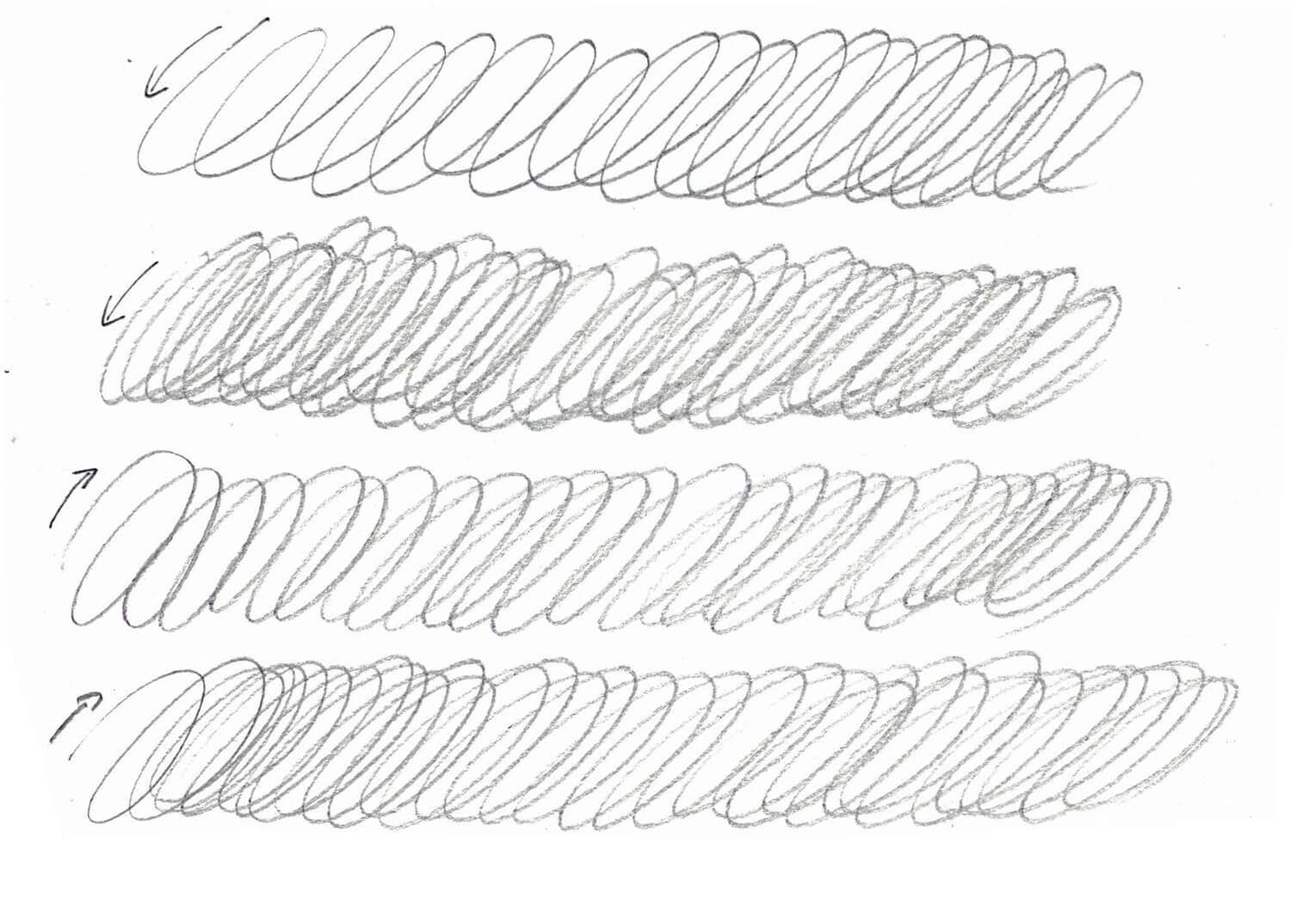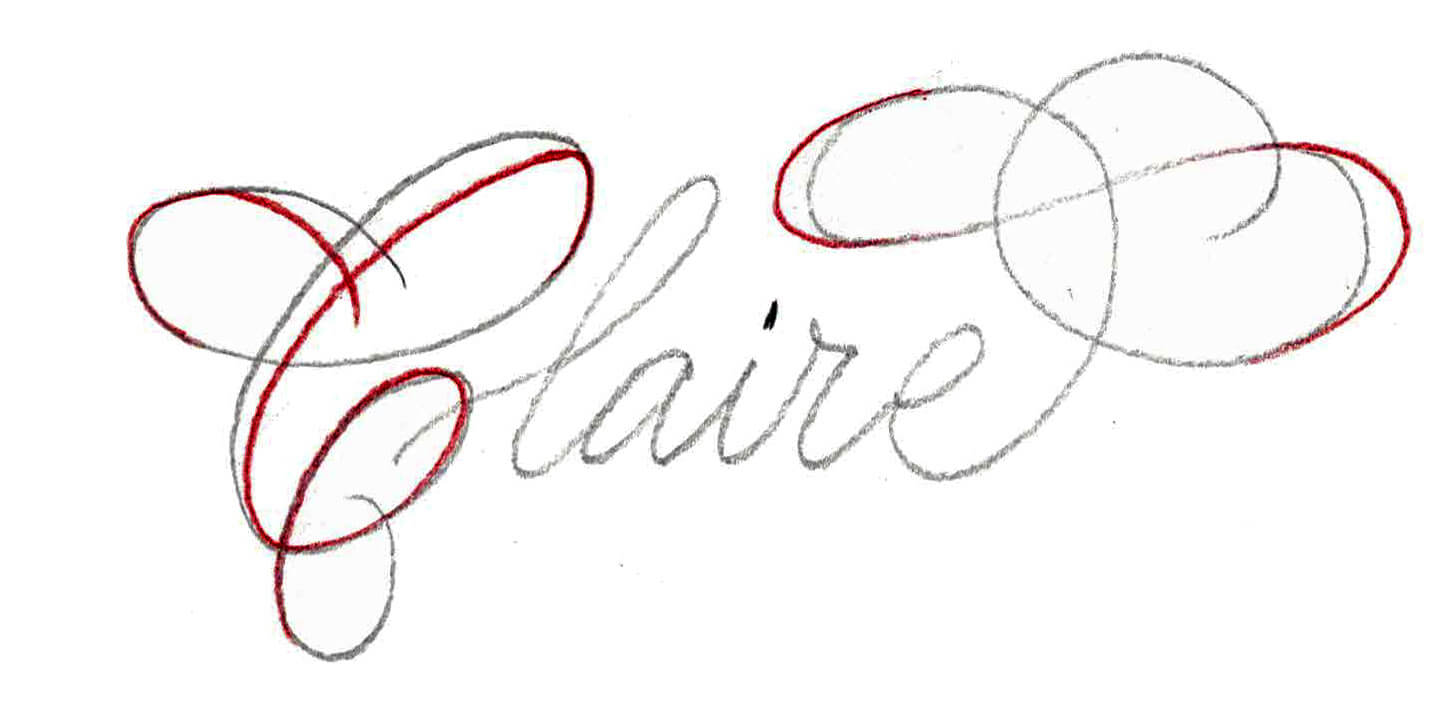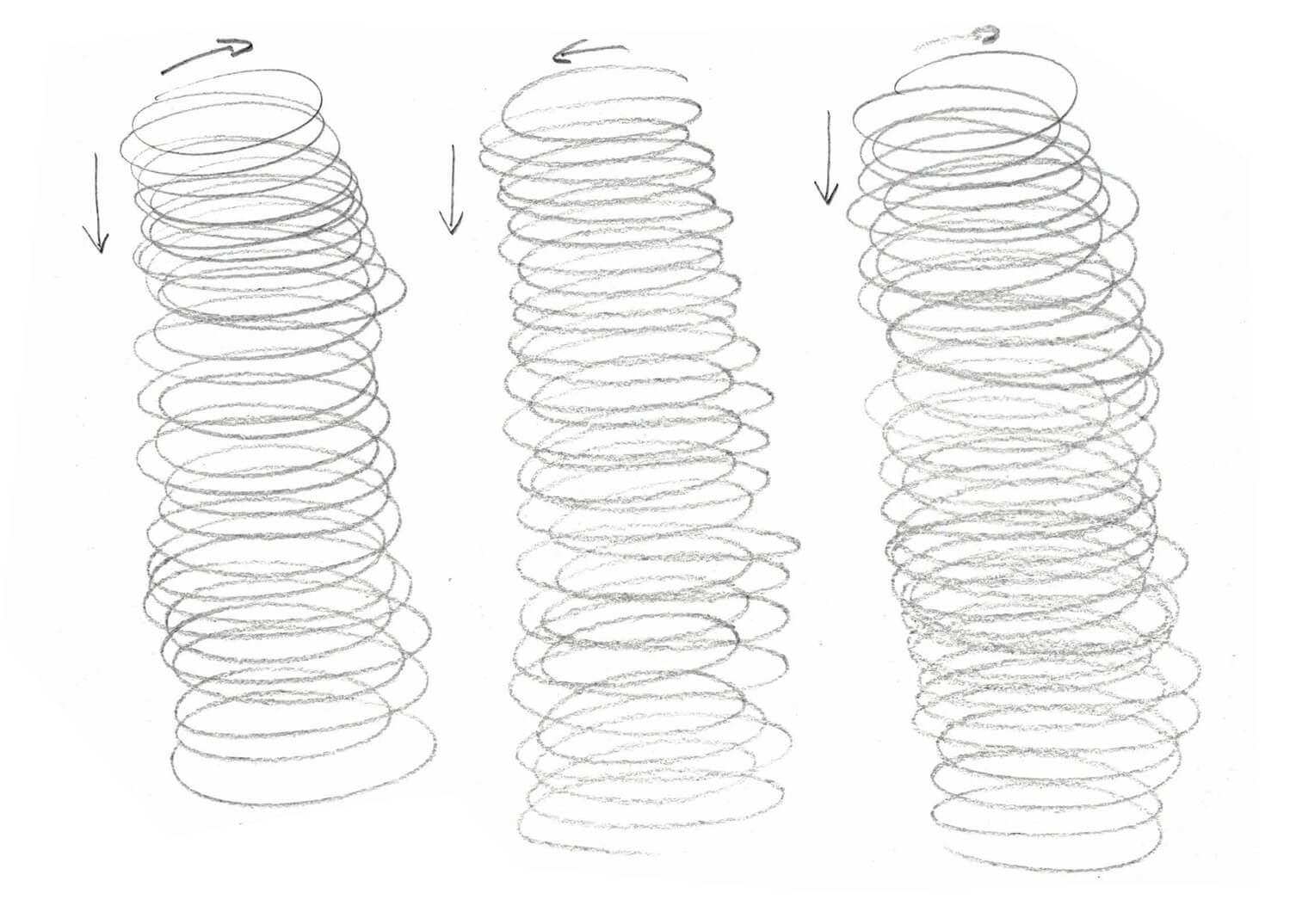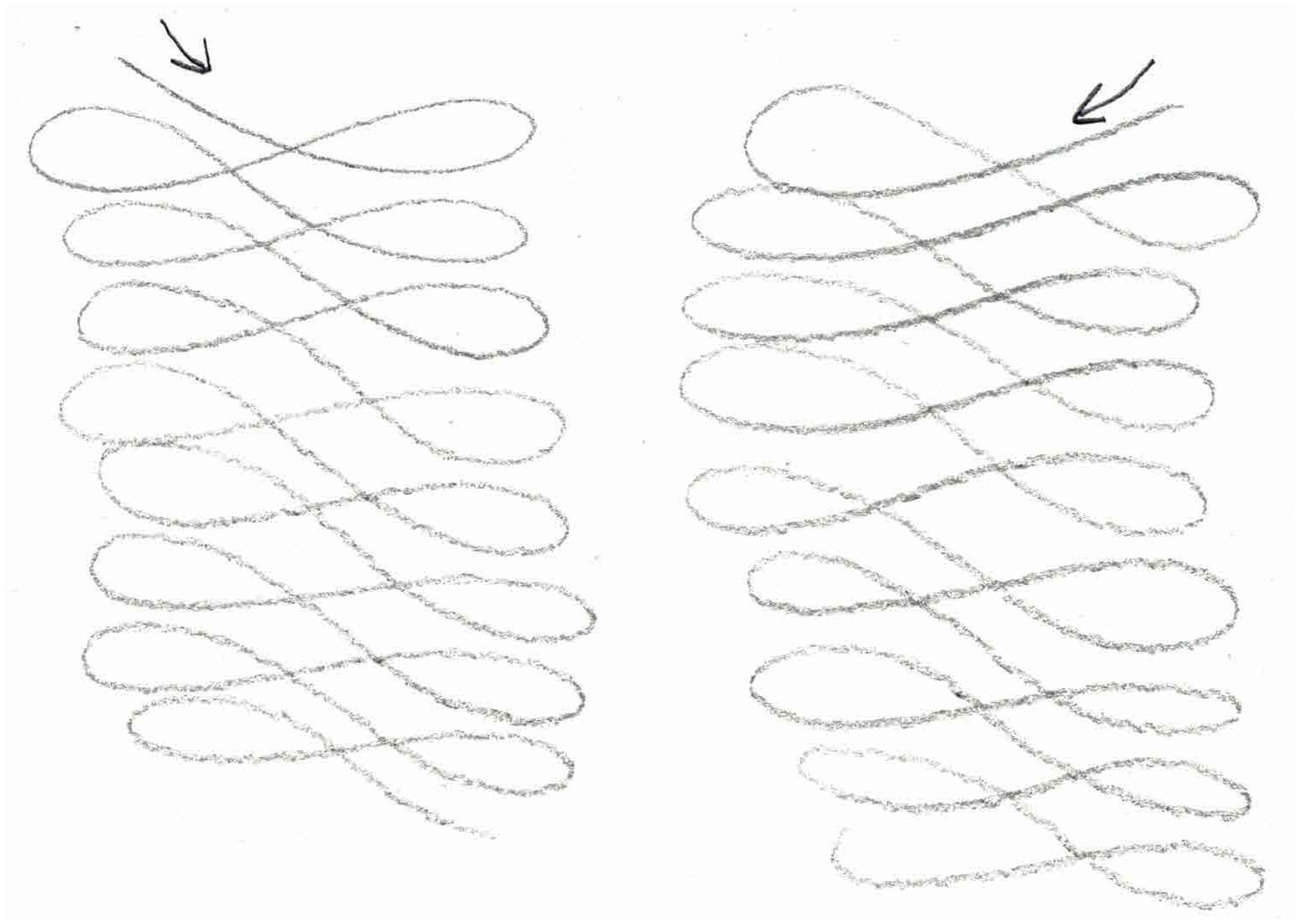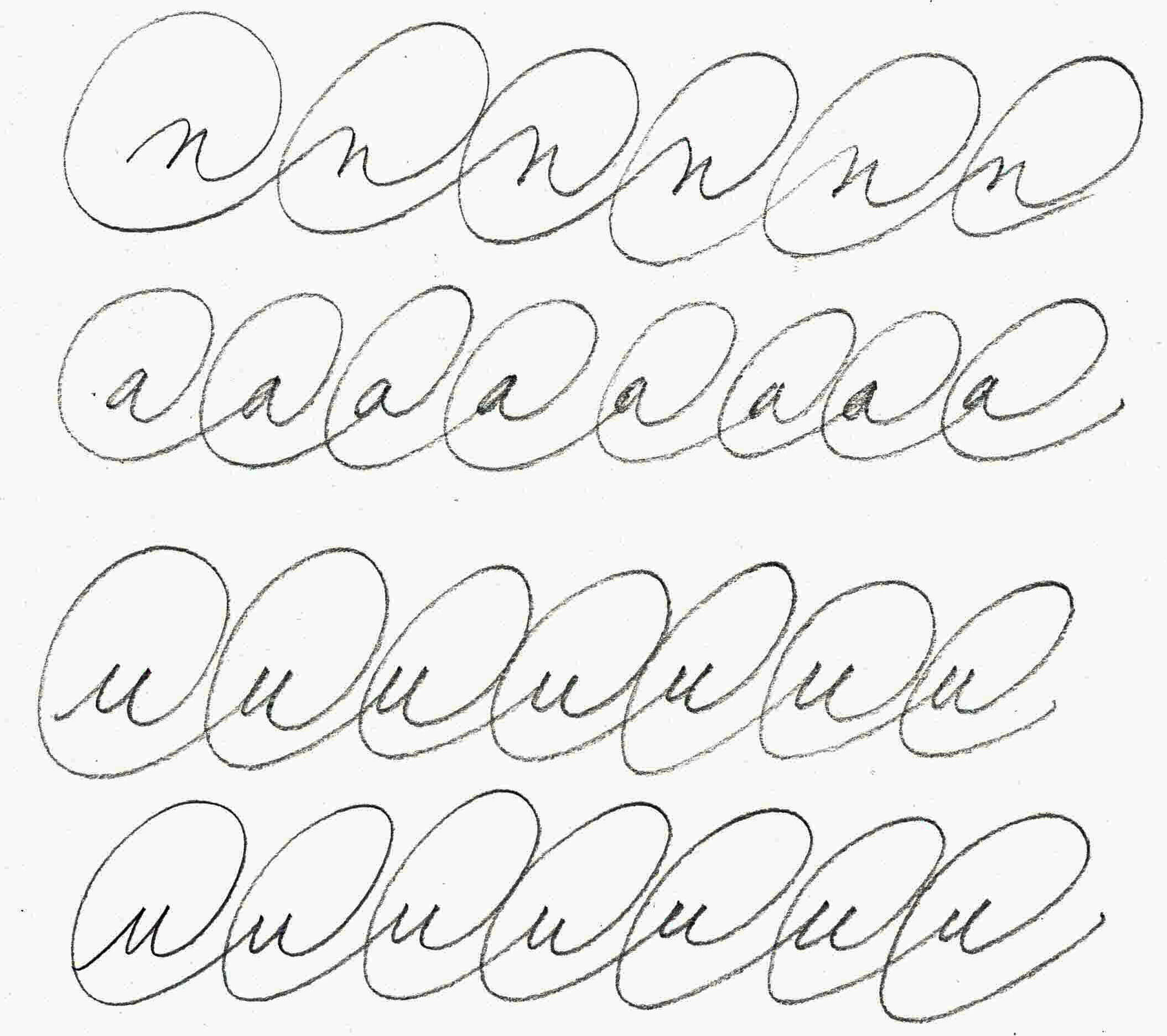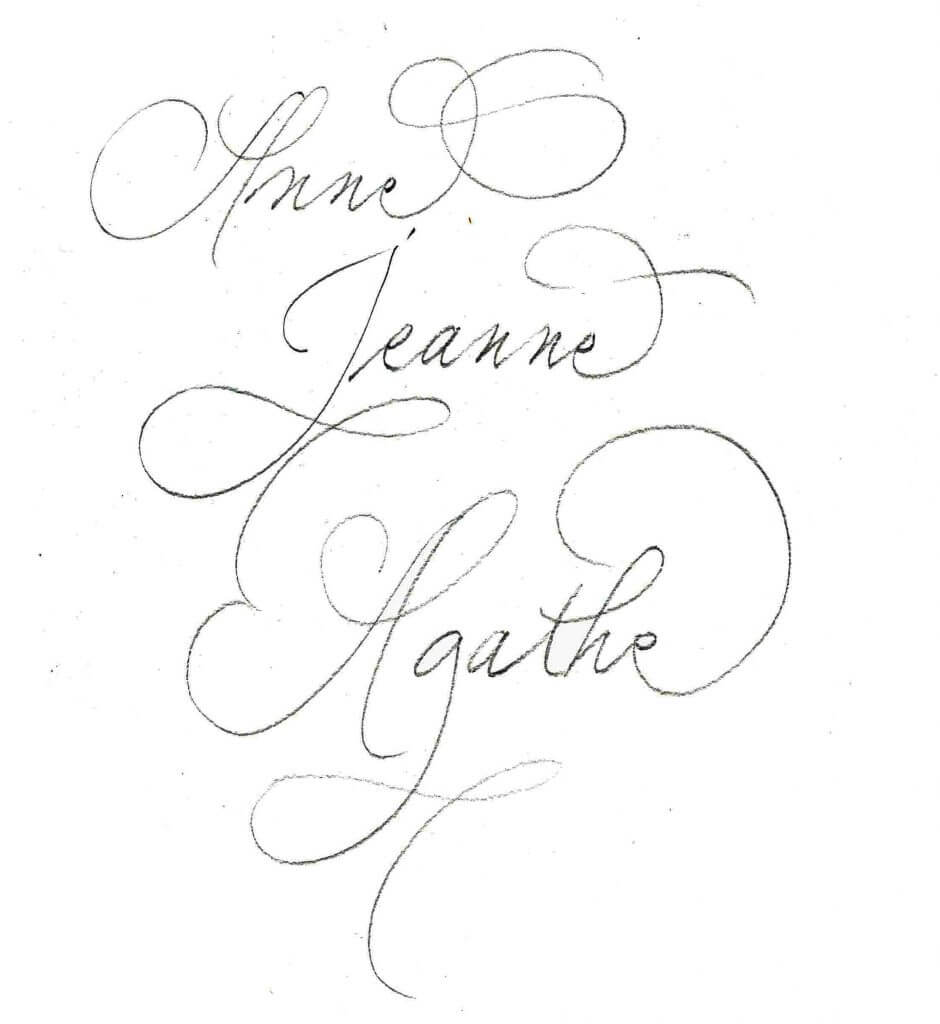
Si vous pratiquez la Copperplate (ou anglaise); vous avez certainement entendu parlé de Flourishing, que l’on pourrait traduire par « fleurissement ». Ce terme est utilisé par les anglo-saxons pour désigner les arabesques qui ornent l’écriture anglaise. Loin d’être exécutées au hasard, elles répondent à un équilibre subtil de mouvements et de formes.
Evidemment, en commençant l’anglaise, j’ai voulu me lancer dans ces belles volutes. J’ai vite déchanté car bien sûr, cela ne se fait pas en claquant des doigts. Il m’a fallu du temps pour comprendre pourquoi je ne pouvais pas reproduire d’emblée des modèles, pourquoi c’était moche, alors que sur Instagram je voyais des vidéos qui laissaient croire que c’était trop facile.
Petite leçon au passage : ne pas se laisser berner par des vidéos, même d’amateurs ! Derrière ces quelques secondes de pure glisse, des années de pratique, des kilomètres de labeur.
De plus les livres de calligraphie en français sont plutôt sibyllins sur la question. Les livres en anglais n’en disent pas beaucoup plus. Du coup, j’ai commencé à m’entraîner comme j’ai pu. Pour cela j’ai laissé momentanément la plume pour prendre un crayon de papier (HB/B). L’objectif étant d’acquérir le mouvement et les formes, j’ai opté pour un outil plus simple d’utilisation que la plume. Disons aussi un outil qui suscite moins d’appréhension, pour être plus libre.
Je vous explique ci-dessous mon cheminement, si cela peut vous aider. Autant dire que je ne suis pas au bout du chemin, donc tout ce qui est expliqué ci-dessous reste à ce stade un partage pour qui veut.
Exercices d’échauffement au crayon de papier
La base des arabesques : l’ovale
Pour commencer notre échauffement, je vous propose de tracer des ovales sur le même axe, sans effet de plein ou de délié. Vous pouvez les démarrer en partant de bas en haut, puis du haut vers le bas. Essayez d’avoir un mouvement régulier, ni trop lent, ni trop rapide, et un trait léger. Ce qui est important, c’est que ce soient votre bras et votre épaule qui dirigent le mouvement, et non le poignet. Le bras ne doit pas être en appui sur la table. De ce fait, la main, les doigts et le poignet sont assez immobiles, en prolongement du bras qui bouge.
Si vous répétez cet exercice vous constaterez qu’au bout de quelques lignes votre forme est plus régulière.
Vous pouvez ensuite faire ce même exercice, toujours pour vous échauffer, de haut en bas.
Les zigzags et les premières arabesques
A ce stade, vous avez normalement « libéré votre bras » et votre cerveau commence à coordonner le mouvement. Ah oui, parce que je ne vous l’ai pas dit : faire des arabesques c’est avant tout un exercice psycho-moteur, un exercice de coordination et de mémorisation de mouvements « types ». D’où la nécessité de s’entraîner.
Bref, c’est parti pour des zigzags!
… qui peu à peu commencent à ressembler à des arabesques :
Notez que le mouvement est très léger, comme si la main volait au dessus du papier. A ce stade, toujours pas d’effets plein/délié.
Exercice pour préparer l’enchaînement lettre-arabesque
Cet exercice permet de se préparer à enchaîner une arabesque à la fin d’un mot, par exemple. Il provient directement de mes cours de gestuelle, mais trouve toute sa place ici, vous comprendrez vite pourquoi.
Pour se faire, tracer une lettre encapsulée dans une boucle, comme une arobase. Le « u » est une bonne lettre pour l’exercice. Pour varier, faites plusieurs lignes en changeant de lettre. Ce qui est important ici, c’est que l’enchaînement lettre/boucle se fasse d’un trait. Donc on fera plutôt une pause avant de tracer le dernier jambage de la lettre, puis on tracera le dernier jambage + la boucle en une fois.
Après, on peut commencer une vraie arabesque en sortie de mot :
J’ai pris le « u », mais vous pouvez bien sur choisir d’autres lettres. La première tentative en haut à gauche est toute moche, puis ça s’améliore… C’est aussi parce que mon mari est venu m’interrompre en plein élan dans cette première lettre 😉
Exemple de variation avec la barre du « t » :
En rouge, une auto-correction
Arabesques en début de mot (majuscules)
Pour s’entraîner à faire des boucles pour les majuscules, on s’échauffe aussi avec des ovales, mais de droite à gauche cette fois-ci. Dans l’exemple ci-dessous, je les ai tracées au crayon de couleur, en travaillant un peu plus la pression pour obtenir un plein et un délié.
Ce qui importe, dans cet exemple, c’est que l’axe des boucles soit bien le même.
Ce qui importe aussi, c’est que le trait soit vif, sûr sans être raide. La boucle de gauche laisse un peu à désirer de ce côté-là.
Poursuivre l’entraînement avec des mots
Vous pouvez ensuite commencer à vous exercer avec des mots simples, toujours au crayon.
Ici pas de lignes, vous l’avez remarqué : l’objectif est vraiment d’imprimer un mouvement et de libérer le bras. Les anglo-saxons appellent d’ailleurs cela « off-hand calligraphy », ou calligraphie à main levée, ce qui veut tout dire.